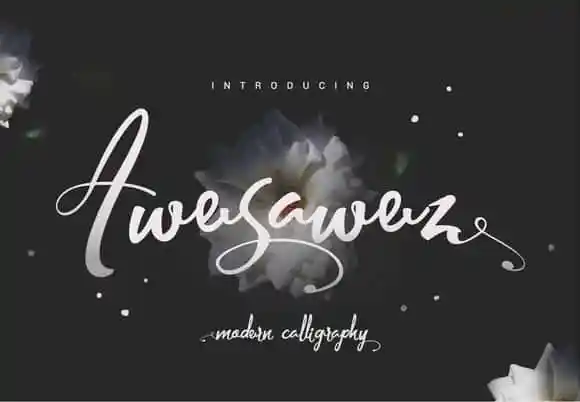
Awesawez Script Font – Download Grátis
Awesawez é uma tipografia de script que captura a essência do estilo à mão com movimentos fluidos e curvas arredondadas. Suas linhas exuberantes criam um charme único, tornando-o perfeito para destaque seus textos – seja em logotipos, cartões de visita, convites ou embalagens de produto. O seu poderoso impacto visual torna o Awesawez uma escolha ideal para gráficos de cabeçalho e qualquer obra que você possa imaginar trazer à vida com suas letras. Para os designers em busca de algo surpreendentemente criativo e divertido, esta fonte é um verdadeiro tesouro.